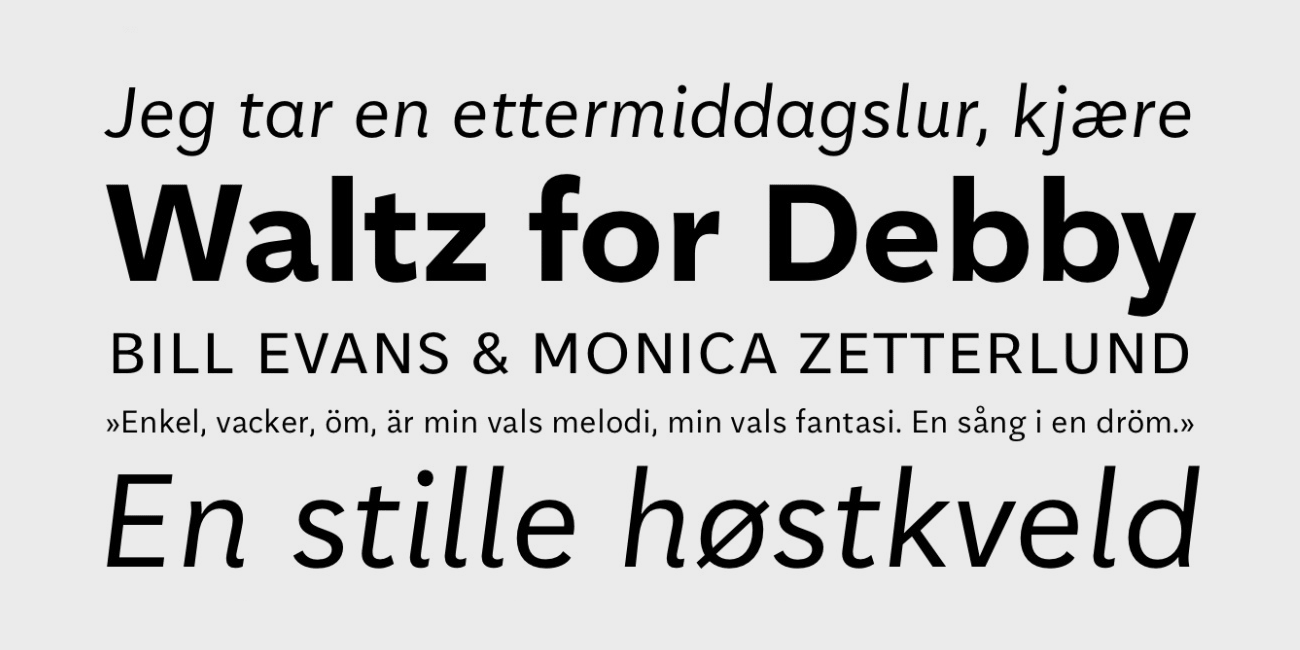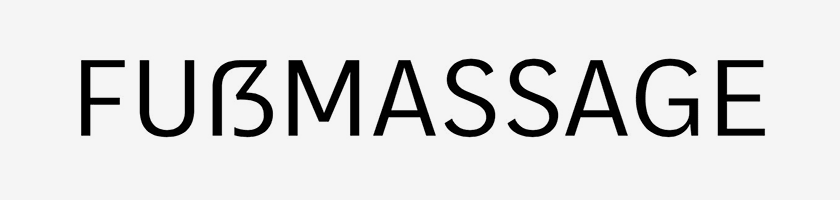
Font-Wiki: Aften Screen
Aften wurde speziell dafür entworfen, in kleinen Lesegrößen gute Ergebnisse am Bildschirm zu erzielen. Ihre drei Schriftschnitte (Regular, Kursiv, Fett) sind deshalb als Web- und App-Fonts verfügbar.